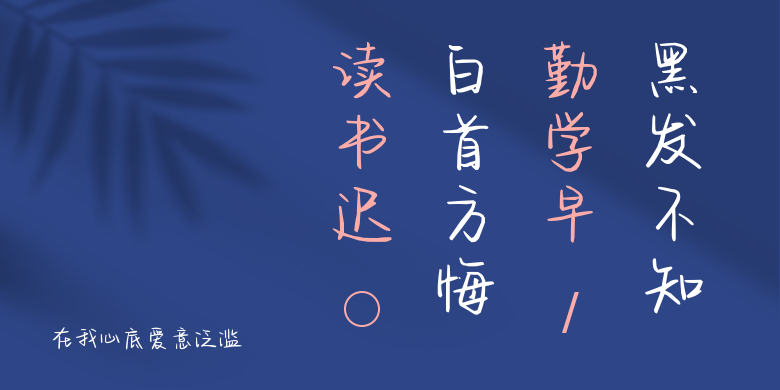
在我心底爱意泛滥
在我心底爱意泛滥,这款字体结构工整、笔画清晰,兼顾美观与易读性,适用于标题、正文、海报、包装、LOGO 等多种场景。字形优雅稳定,风格百搭耐看,适配日常排版与创意设计,让文字呈现更舒适、更具质感。在我心底爱意泛滥一笔一画,皆是细节,以均衡的比例、流畅的线条打造舒适视觉体验,字形端正大气,风格简约现代。无论是商业设计、品牌宣传还是日常排版,都能轻松驾驭,让文字更有格调与力量。在我心底爱意泛滥字体下载。